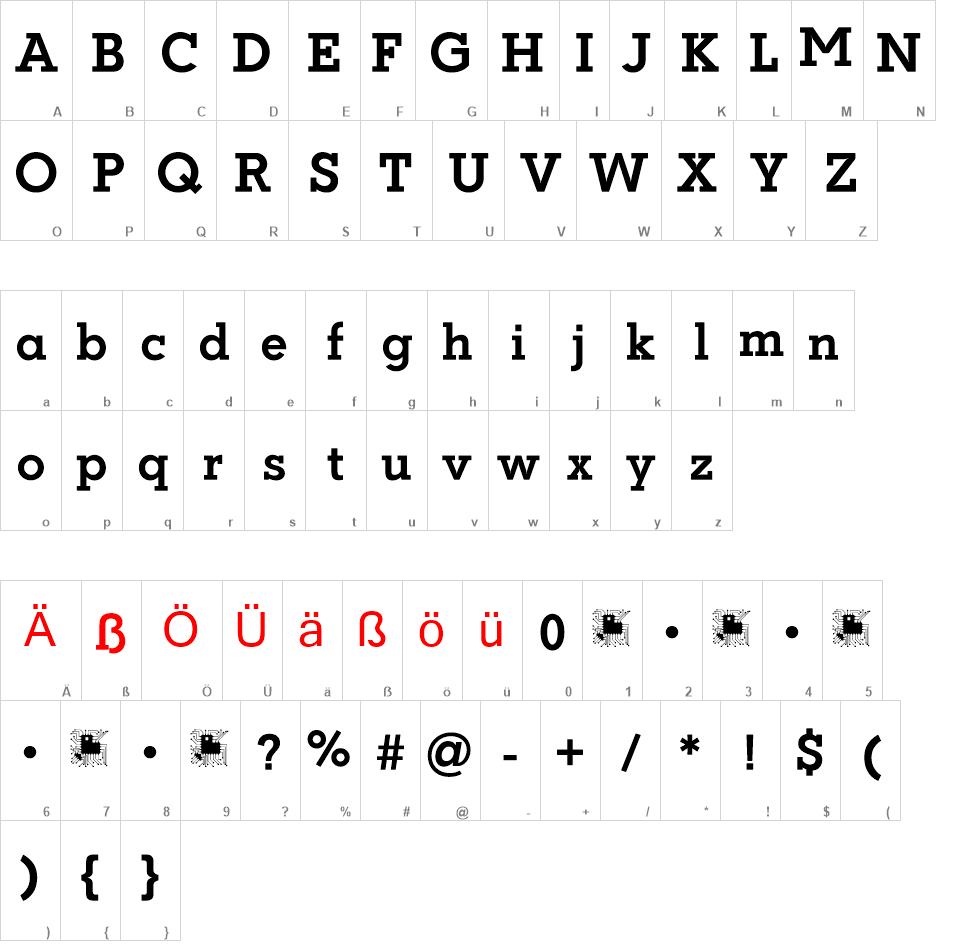
Coltan Gea
Coltan Gea ist eine Slab Serif typografische Familie mit 6 Gewichten plus die kursiven Versionen enthalten alle kleine Großbuchstaben und Kryptowährung Symbole.
Es ist eine geometrische, minimalistische Schrift mit neo-grotesken Modulationen und leicht abgerundeten Ecken. Die Schrift verfügt über alternative Buchstaben und Zahlen, Kapitälchen und erweiterte OpenType-Funktionen. Die Proportionen, Metriken und Kerning habe ich akribisch für eine perfekte Lesung in jeder Größe konfiguriert.